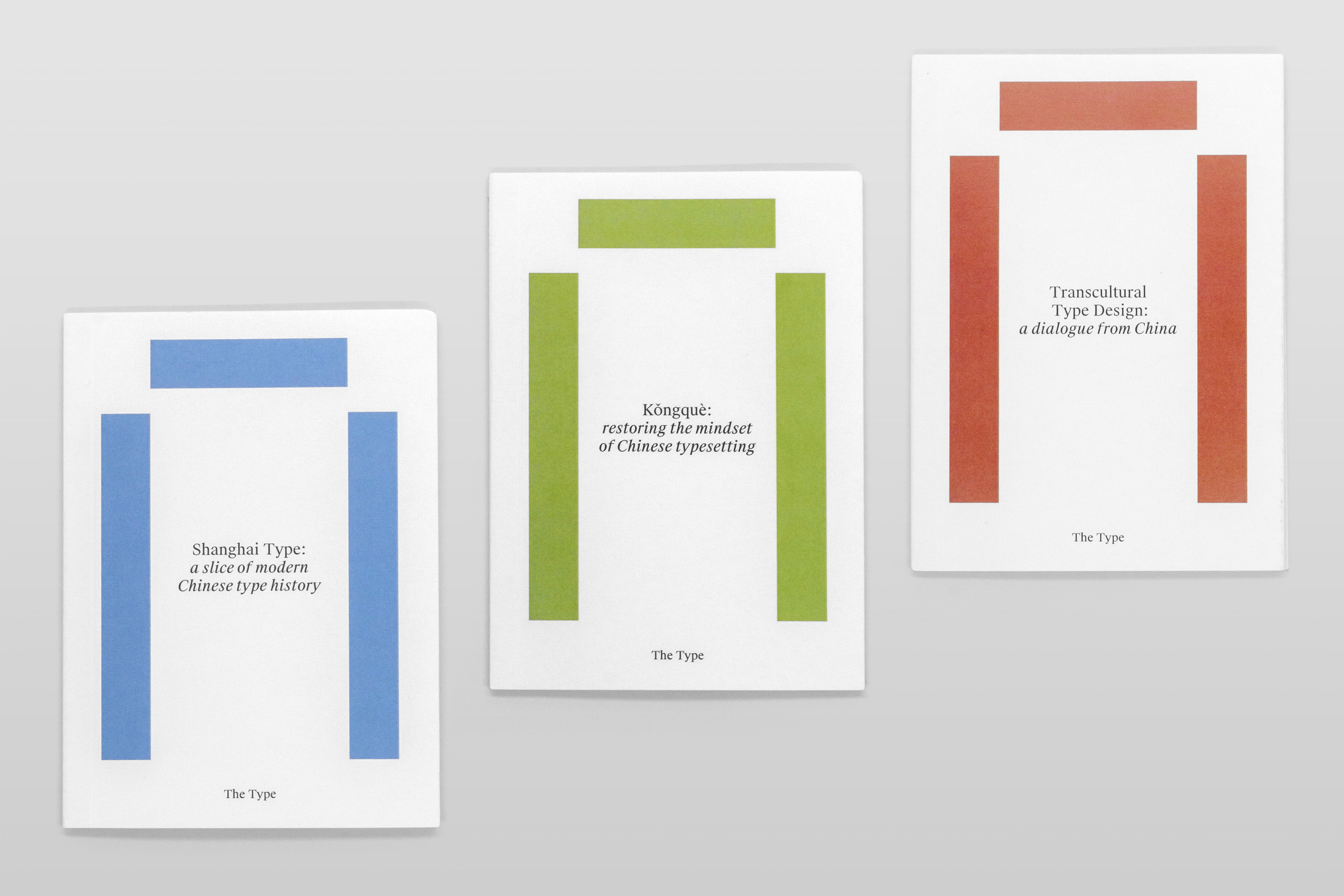
十多年來,The Type 一直在中文領域推動公眾對字體排印、文字設計的認知。從最初引介西方字體排印理論和知識,到近年來開始針對中文字體領域做獨立研究,我們愈加意識到中文設計基礎教育的匱乏,與國際相關領域的交流渠道也比較單一。雖然中文設計是一個較難入門的領域,但我們相信,進行更自主、更公開的研究、並且將中文設計面臨的挑戰放到全球視角下共同探討,能為我們自己的文字設計帶來更多突破。
這三本手冊便是 The Type 正在進行的多個中文設計研究項目的選集,話題包括了中文字體設計歷史與發展、中文排版傳統與當代實踐、以及中文語境下對跨文化設計的討論。
We at The Type have been promoting public awareness of typography and design in the Chinese community for over ten years. Whether it is introducing Western typography theories and knowledge, or conducting independent research on Chinese typography in recent years, we are often concerned about the inadequate typography education in China as well as the lack of exchange we have with the international community. Chinese typography is not easy to tackle, but we believe that, by more self-initiated and open research, we are able to address our challenges under a global perspective and invite more discussions and breakthroughs to the field.
So here is a three-volume collection of our on-going research and dialogues about typography and design in China, including its history and development, conventions and contemporary practice, and working in transcultural contexts.
內容簡介
Content
上海活字:管窺現代中文字體設計史
Shanghai Type: a slice of modern Chinese type history
建國後的中文字體設計發展,對當代影響深遠,但這段歷史對於許多國內外設計師來說都是陌生的。在「上海活字」研究項目的努力下,我們試圖勾勒出現代中文字體設計的歷史,了解它最初如何成為由國家層面推動的創舉,其地位又如何在市場和商業化的激流中逐漸消退。
The development of Chinese type design since the foundation of the People’s Republic in 1949 cast significant influence to its contemporary developments. Yet it has remained as much a mystery to the outside world as to local designers. Thanks to the research throughout the Shanghai Type project, we attempt to illustrate a slice of the history of how modern Chinese type design began as a groundbreaking state-initiated endeavour, and then gradually faded in the age of market and commercialisation.
孔雀計劃:重建中文排版的思路
Kǒngquè: restoring the mindset of Chinese typesetting
中文漢字排印幾百年來的傳統和智慧,並沒有在當今的設計實踐中得到傳承。究其原因,目前計算機軟件的邏輯都建立在拉丁文字系統的基礎上,而國內的設計教育也忽略了這一方面。孔雀計劃旨在通過回顧中國文字排印的歷史,填補這塊空白,並在現代的設計環境下重建起本土的中文排版思路。
The convention and wisdom of Chinese typography that was developed over centuries has failed to be inherited by designers today’s designers. This is caused partially by the Latin-orientated computer softwares and the negligence in the Chinese design education. Kǒngquè project aims to fill this gap by revisiting the typographic traditions in China in the modern context and restoring a mindset of native Chinese typography.
跨文化字體設計:中文語境下的討論
Transcultural Type Design: a dialogue from China
在中文設計師群體中,圍繞跨文化文字設計進行的探討還不成氣候。這本小冊子是我們針對這一話題組織的一系列討論的記錄之一,主要着眼於跨文化設計這一全球趨勢,以及它在中文語境下帶來怎樣的爭辯和策略。
Among the Chinese-speaking designers, discourse around transcultural typography is still in its infancy. This small volume is the record of the first of a series of open discussions moderated by us, to address this global trend as well as the debate and strategies that come along in the Chinese context.